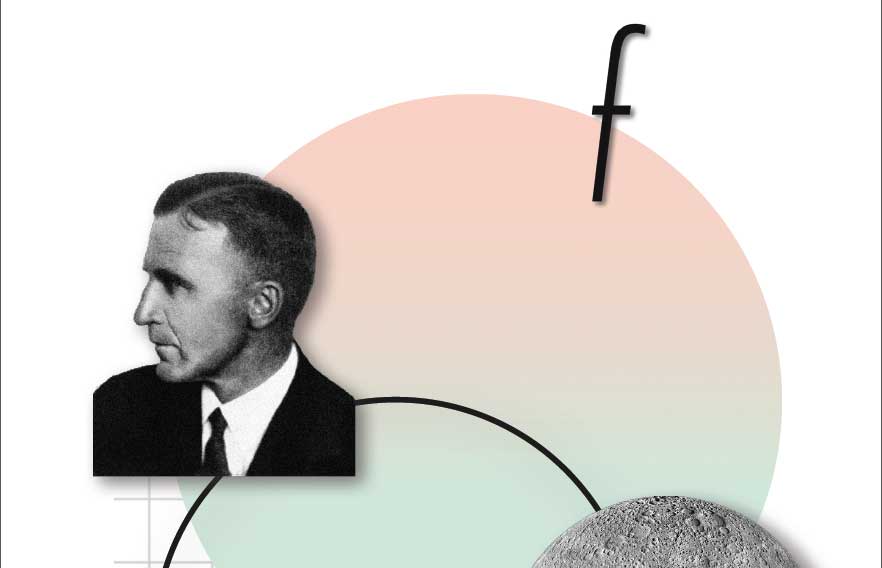
Futura-SymposiumFUTURA—TRIBUTE TO A TYPEFACE
FUTURA: Die »Zukünftige«. Unter diesem Namen veröffentlichte der Typograf und Schriftgestalter Paul Renner 1927 seine neue Schrift bei der Bauerschen Giesserei in Frankfurt am Main. Entwickelt im Kontext der Neuen Typografie, gilt sie bis heute als die wohl bekannteste und wirkungsvollste deutsche Schrift.
Was ist das Erfolgsgeheimnis dieser geometrischen Sans Serif? Sicherlich nicht nur ihr Name, der sie immer wieder aufs Neue für Zukunftsprojekte – etwa die Mondlandung 1969 – prädestinierte. Ein großer Teil ihres Erfolges dürfte auch ihrer zeitlosen Eleganz geschuldet sein, die es erlaubte, diese Schrift gestalterisch immer wieder überraschend neu und ästhetisch überzeugend einzusetzen. Und das bis heute.
Das Translations 5 Symposium unter dem Titel FUTURA – TRIBUTE TO A TYPEFACE stellt aktuelle Positionen im Type und Corporate Design vor, die sich begeistert auf die berühmte geometrische Sans Serif beziehen oder aber sich von ihr inspirieren lassen. Vorgestellt und diskutiert werden aber auch kritische Positionen sowie neue designhistorische Forschungsergebnisse zur Entstehungs- und Rezeptionsgeschichte.